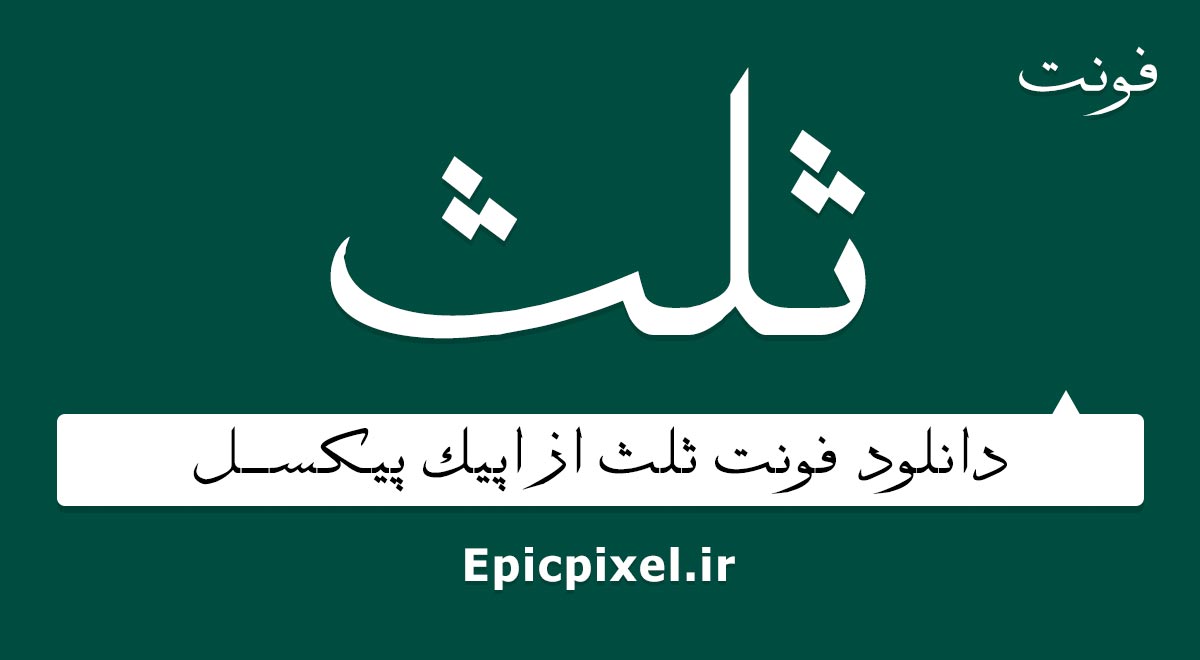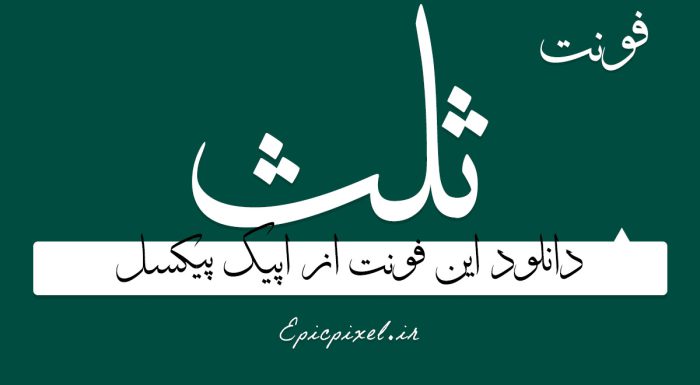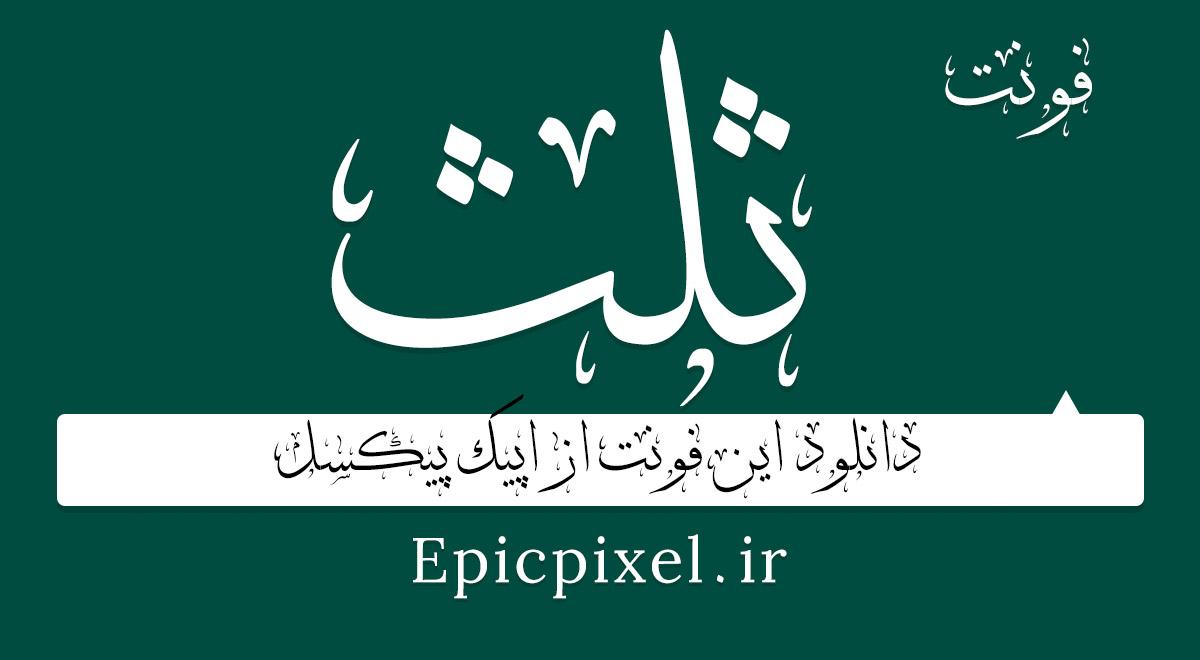
مجموعه فونت ثلث فارسی (Thuluth)، یک پکیج جامع برای طراحان و علاقه مندان به خوشنویسی اسلامی است که شامل حدود 32 فونت متنوع بر اساس خط ثلث می باشد. این خط با ساختاری ایستا و موقر و الف های بلند (هفت نقطه ارتفاع) شناخته می شود و القاکننده قدرت و عظمت است. فونت های این مجموعه در فرمت TTF ارائه شده، برای طراحی های گرافیکی، کتیبه ها، عناوین مذهبی و چاپ مناسب هستند. این مجموعه فونت برای دانلود در دسترس بوده و امکان استفاده از زیبایی خط ثلث را در نرم افزارها و روی پلتفرم های مختلف (ویندوز، iOS، اندروید) فراهم می کند، اگرچه ممکن است در سازگاری با نرم افزارهای گرافیکی حرفه ای نیازمند ترفندهایی باشد.
مجموعه کامل فونت ثلث فارسی (Thuluth)، یک پکیج وسیع برای علاقه مندان به خوشنویسی اسلامی و استفاده از این خط با شکوه در طراحی های دیجیتال و چاپی است. این مجموعه شامل حدود 32 فونت با اسم ثلث می باشد و تنوع بالایی را در پیاده سازی این خط با سبک ها، وزن ها و ویژگی های مختلف ارائه می دهد. این مجموعه شامل فونت هایی با نام های مختلفی است که این تنوع به طراحان اجازه می دهد متناسب با نیاز پروژه خود، فونت ثلث مناسب را انتخاب کنند.
خط ثلث (Thuluth)، یکی از شیوه های بسیار مهم در خوشنویسی اسلامی و یکی از خطوط ششگانه اصلی است که جایگاه ویژه ای در فرهنگ و هنر اسلامی دارد. ابداع آن را به ابوعلی بن مقله بیضاوی شیرازی در قرن سوم هجری نسبت می دهند و تکامل تدریجی آن به عنوان خطی تزئینی توسط ابن مقله، ابن بواب و یاقوت مستعصمی ادامه یافت. ابن بواب زیبایی و ظرافت را با خط ثلث همراه کرد و به آن شکوه بیشتری بخشید که در طول قرون متمادی مورد تحسین بوده است.
این خط دارای ساختاری ایستا و موقر است و به دلیل الف های بلند (هفت نقطه ارتفاع) نسبت به خطوطی نظیر نسخ و نستعلیق و رقعه، بلندتر است و حس اقتدار را منتقل می کند. خط ثلث خطی است ایستا و ریتمی که در اثر تکرار ضربه های عمودی و بلند حروف در این خط ایجاد می شود و القاکننده قدرت و عظمت است، خصوصاً در کتیبه های ابنیه مذهبی. دارای خطوط منحنی و پیچیده ای است که به آن زیبایی و شکوه می بخشد و از نظر بصری بسیار غنی است. کلمات در این خط گاهی مجزا و گاه خیلی تو در تو و سوار بر یکدیگر نوشته می شوند و دوایر آن نسبتاً کم عمق و باز هستند. این چیدمان هنری می تواند گاهی خوانایی آن کم می شود را در پی داشته باشد، اما زیبایی بصری آن بی نظیر است. خط ثلث دارای بار مذهبی نیرومندی است و برای نوشتن آیات قرآن و متون مذهبی استفاده می شود.
دانلودفونت های ثلث موجود در این مجموعه سعی در بازتولید زیبایی خط ثلث سنتی در قالب دیجیتال دارند و برخی از آن ها بر اساس فونت ثلث یک نرم افزار خاص ساخته شده و با فونت های ثلث های سابق تفاوت دارند. تفاوت های ویژه در برخی از این فونت ها می تواند به قابلیت کشیدگی اکثر حروف (با استفاده از SHIFT+J) اشاره کرد که امکان ایجاد فرم های متنوع تر در تایپ را فراهم می کند و دست طراح را باز می گذارد.
خط ثلث به صورت تاریخی بیشتر در تزئین کتاب ها و کتیبه ها به کار رفته است و در معماری اسلامی جایگاه ویژه ای دارد. در ایران برای نوشتن عنوان سوره های قرآن کریم، پشت جلدنویسی، سرلوحه ها، و بخصوص در کتیبه ها و کاشی کاری ها بکار رفته است و هنوز نیز رایج است و در طراحی های معاصر نیز جایگاه خود را دارد.
با توجه به ماهیت هنری، ساختار موقر و الف های بلند، و بار مذهبی نیرومند، مجموعه فونت های ثلث کاربردهای گسترده ای در طراحی گرافیک و وب دارد. این قلم ها برای تزئین کتاب ها و کتیبه ها، نوشتن عنوان سوره های قرآن کریم، پشت جلدنویسی، سرلوحه ها، و بخصوص در کتیبه ها و کاشی کاری ها استفاده می شوند و هنوز نیز رایج هستند. در طراحی معاصر، در مجله ها، پشت جلد کتاب ها، پوسترها، سرلوحه ها و طرح تمبر، بزرگداشت ها و… مورد استفاده قرار می گیرند. همچنین برای طراحی کتاب ها، کتیبه ها و تابلوها، طراحی های مذهبی، تولید محتوای گرافیکی، طراحی پست اینستاگرام، طراحی پوستر مناسبتی، طراحی لوگو مذهبی و ایجاد طرح های تایپوگرافی (چیدمان حروف) توسط طراحان و گرافیستان به کار می روند. این فونت ها با ساختار قوی و بصری خود می توانند جلوه ای متمایز و پرمعنا به این طرح ها ببخشند.